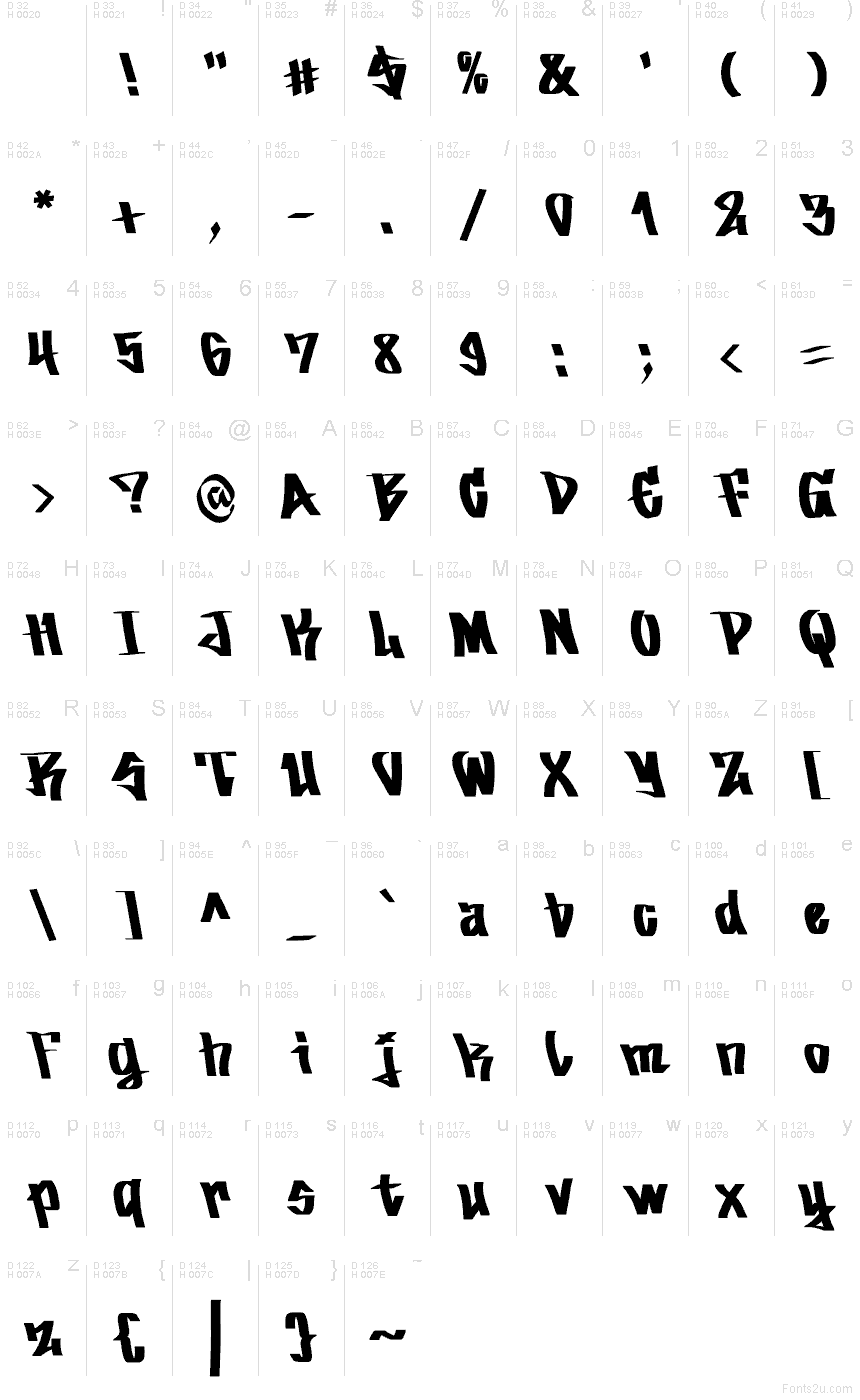
Шрифт Gress Down від Hello Good Studio - це безкоштовний шрифт у стилі графіті з гострими формами та зухвалим ритмом, ніби намальований від руки. Букви виглядають як швидкі мазки пензлем або маркером з кутовими з'єднаннями, нерівними краями та динамічним нахилом, що надає словам руху.
Gress Down чудово підходить для стрітвір-графіки, заголовків на плакатах, обкладинок альбомів, музичного арту та спортивних едитів, оскільки його рвані краї та сміливий силует створюють сирий, урбаністичний тон. Цей безкоштовний шрифт також ідеальний для стікерів, акцентів у логотипах та коротких фраз, де потрібен грубий рукописний ефект без втрати впізнаваного стилю графіті.